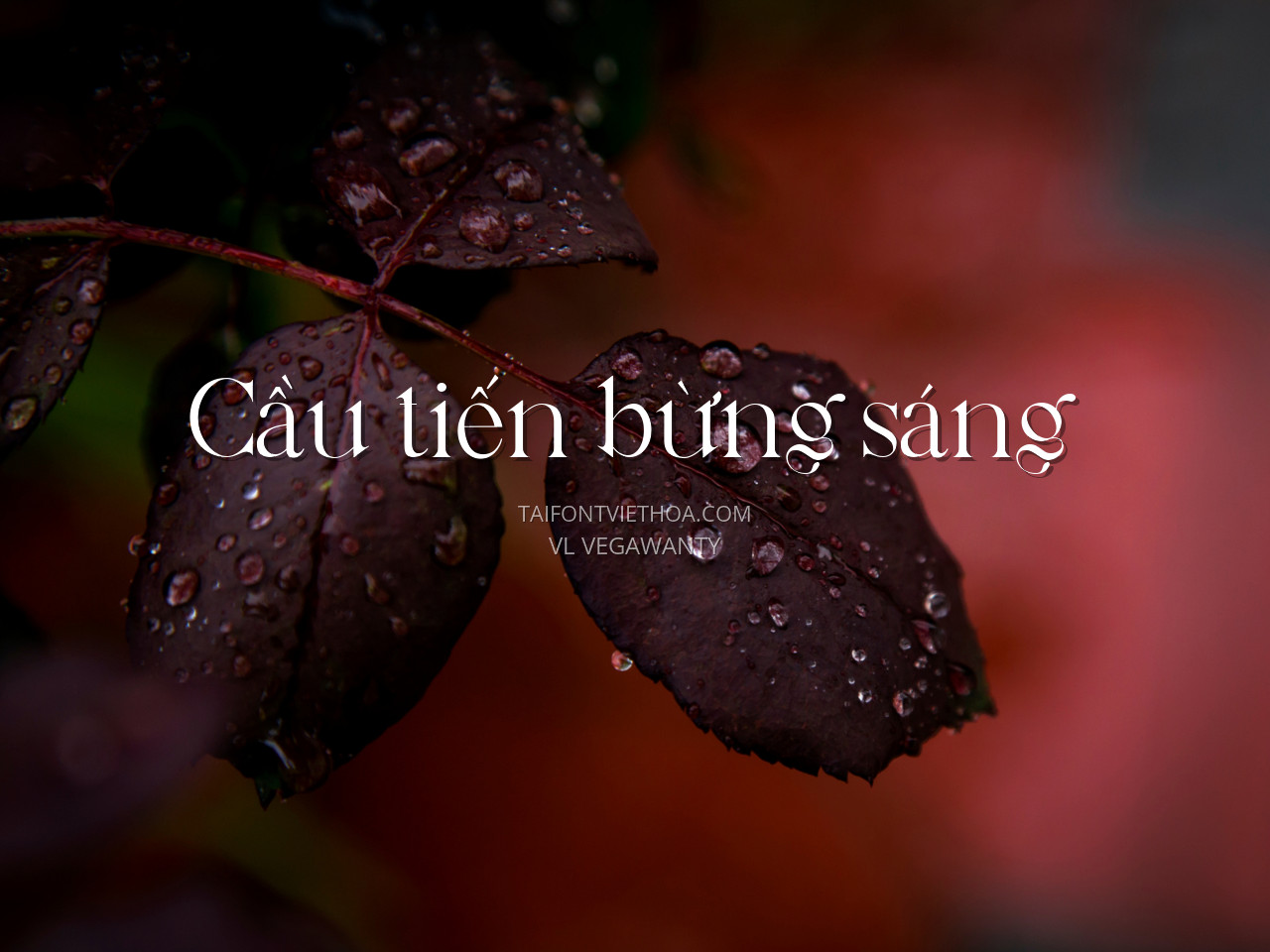
Font việt hóa VL Vegawanty Modern
Giới thiệu về font VL Vegawanty Modern
VL Vegawanty Modern là một font serif cao cấp mang phong cách editorial pha trộn giữa cổ điển và hiện đại. Với các đường nét tinh tế, cấu trúc chữ thanh mảnh nhưng vẫn giữ được độ tương phản mạnh mẽ, font này thể hiện rõ tinh thần sang trọng, chuyên nghiệp và thời thượng. Phiên bản Việt hóa được thực hiện bởi Font Việt Linh, hỗ trợ đầy đủ tiếng Việt với hệ dấu được căn chỉnh chính xác và hài hòa. Ngoài tiếng Việt, font còn hỗ trợ hơn 60 ngôn ngữ khác thông qua bảng mã Latin mở rộng. VL Vegawanty Modern đã được taifontviethoa.com chọn lọc, kiểm thử thực tế và đưa vào ứng dụng trong nhiều dự án thiết kế cao cấp tại Việt Nam.
Đặc điểm thiết kế và ứng dụng của VL Vegawanty Modern
Font sở hữu cấu trúc serif có chân mạnh mẽ với các điểm nhấn sắc sảo, đặc biệt phù hợp cho các tiêu đề, logo hoặc thiết kế cần tạo cảm giác sang trọng và đẳng cấp. Các đường cong và khoảng cách chữ được thiết kế cẩn thận, mang lại khả năng hiển thị ổn định trên cả bản in và nền tảng số.
VL Vegawanty Modern lý tưởng cho các thiết kế branding, poster thời trang, bao bì mỹ phẩm, ấn phẩm truyền thông, bìa sách hoặc website cao cấp. Ngành nghề ứng dụng gồm: thời trang, mỹ phẩm, nội thất cao cấp, bất động sản, xuất bản, giáo dục và truyền thông sáng tạo.